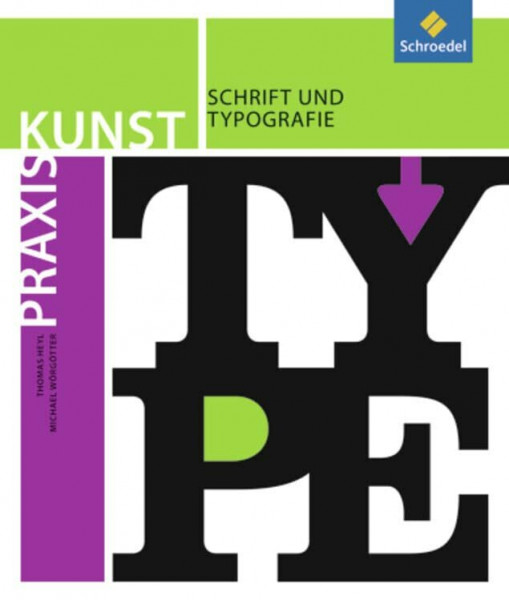
Praxis Kunst - Sekundarstufe II: Praxis Kunst: Schrift und Typografie
"Praxis Kunst - Sekundarstufe II: Praxis Kunst: Schrift und Typografie" von Thomas Heyl ist ein Lehrbuch, das sich an Lehrer und Schüler der Sekundarstufe II richtet. Es bietet eine umfassende Einführung in die Welt der Schrift und Typografie, wobei sowohl theoretische als auch praktische Aspekte behandelt werden. Das Buch erklärt die Geschichte und Entwicklung der Schrift, verschiedene Schriftarten und deren Einsatzmöglichkeiten. Zudem werden gestalterische Prinzipien vermittelt, um den Schülern ein tiefes Verständnis für die ästhetischen und funktionalen Aspekte der Typografie zu geben. Praktische Übungen und Projekte fördern die kreative Anwendung des Gelernten im Unterricht. Das Buch dient somit als wertvolle Ressource für den Kunstunterricht, um Schüler auf anschauliche Weise mit den Grundlagen und Feinheiten der Schriftgestaltung vertraut zu machen.